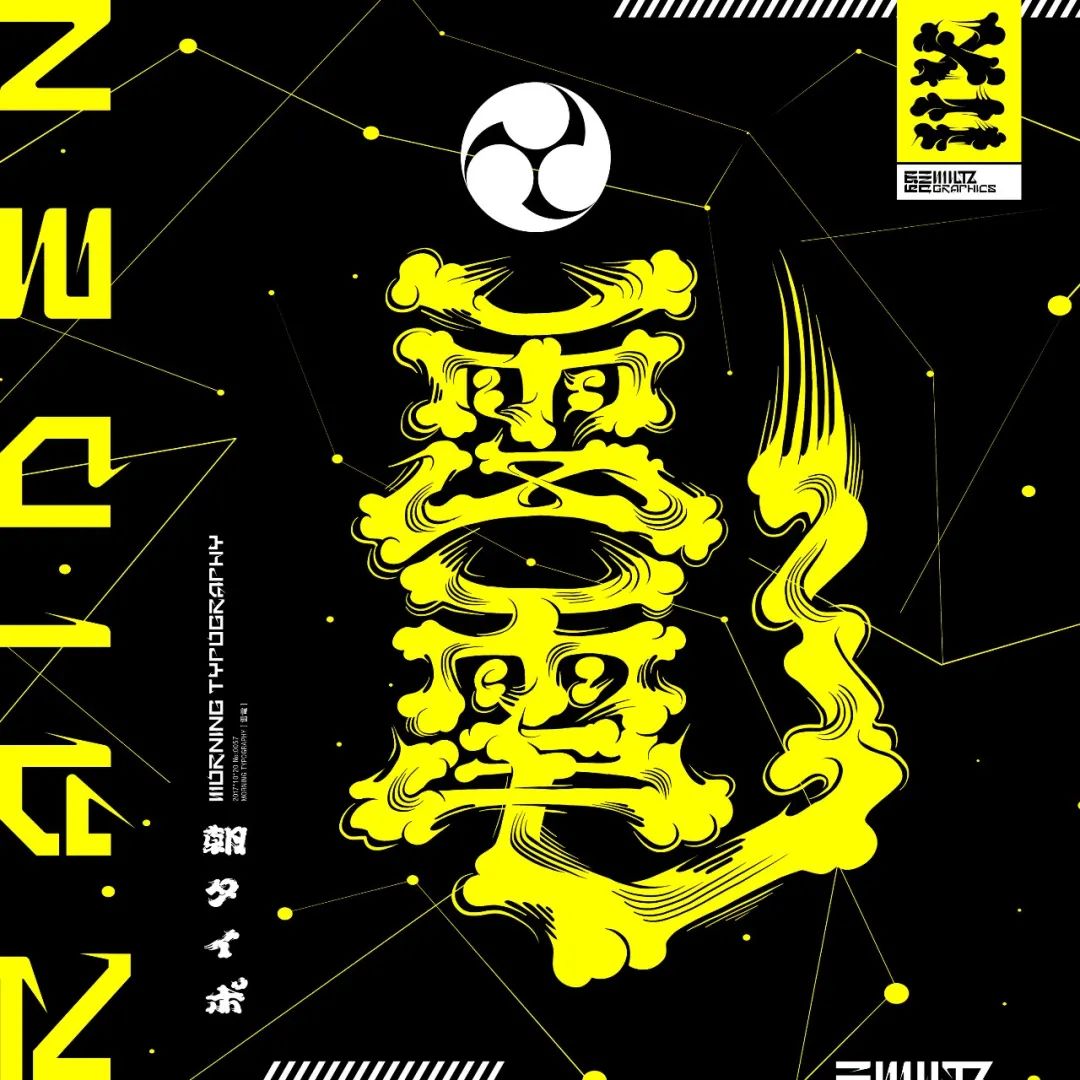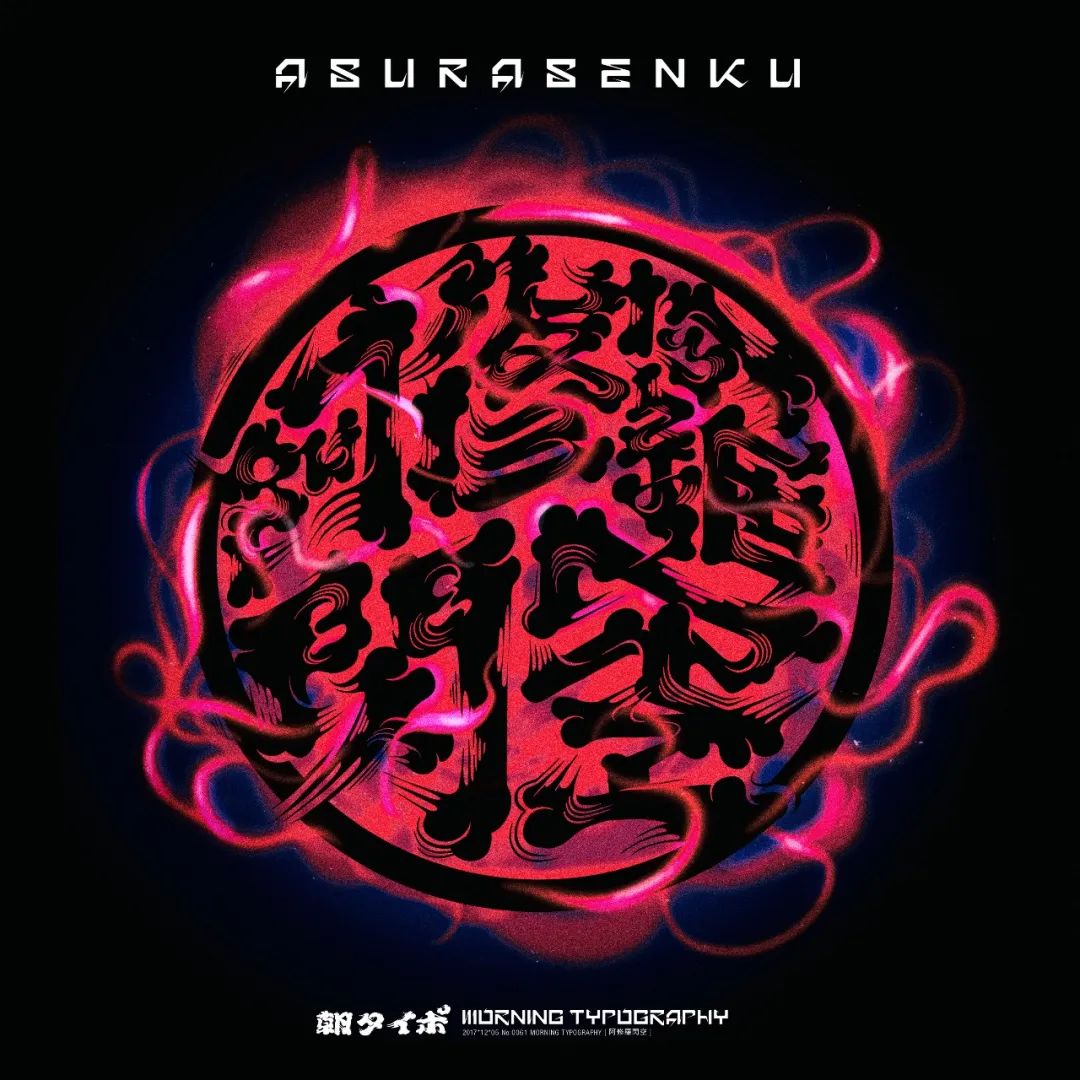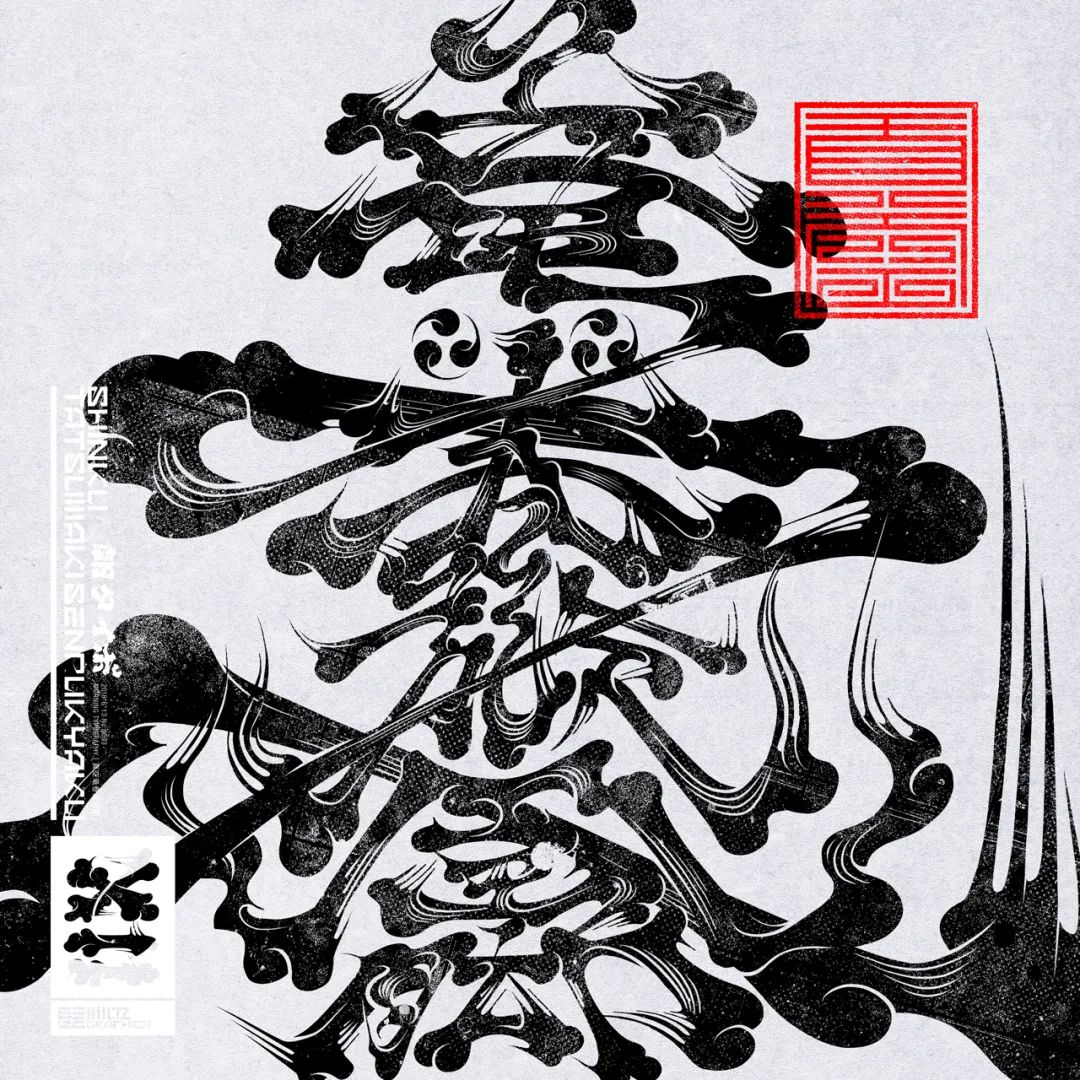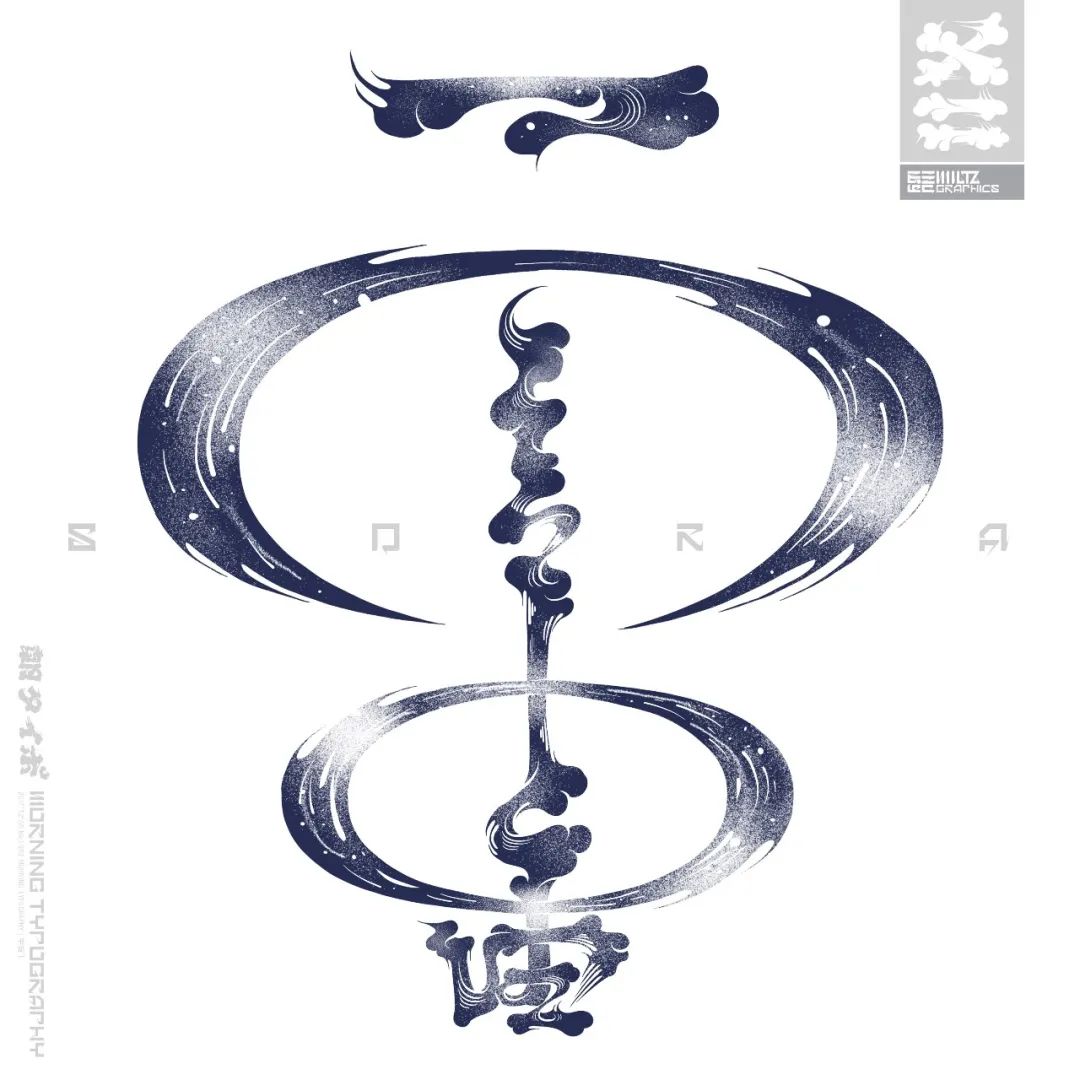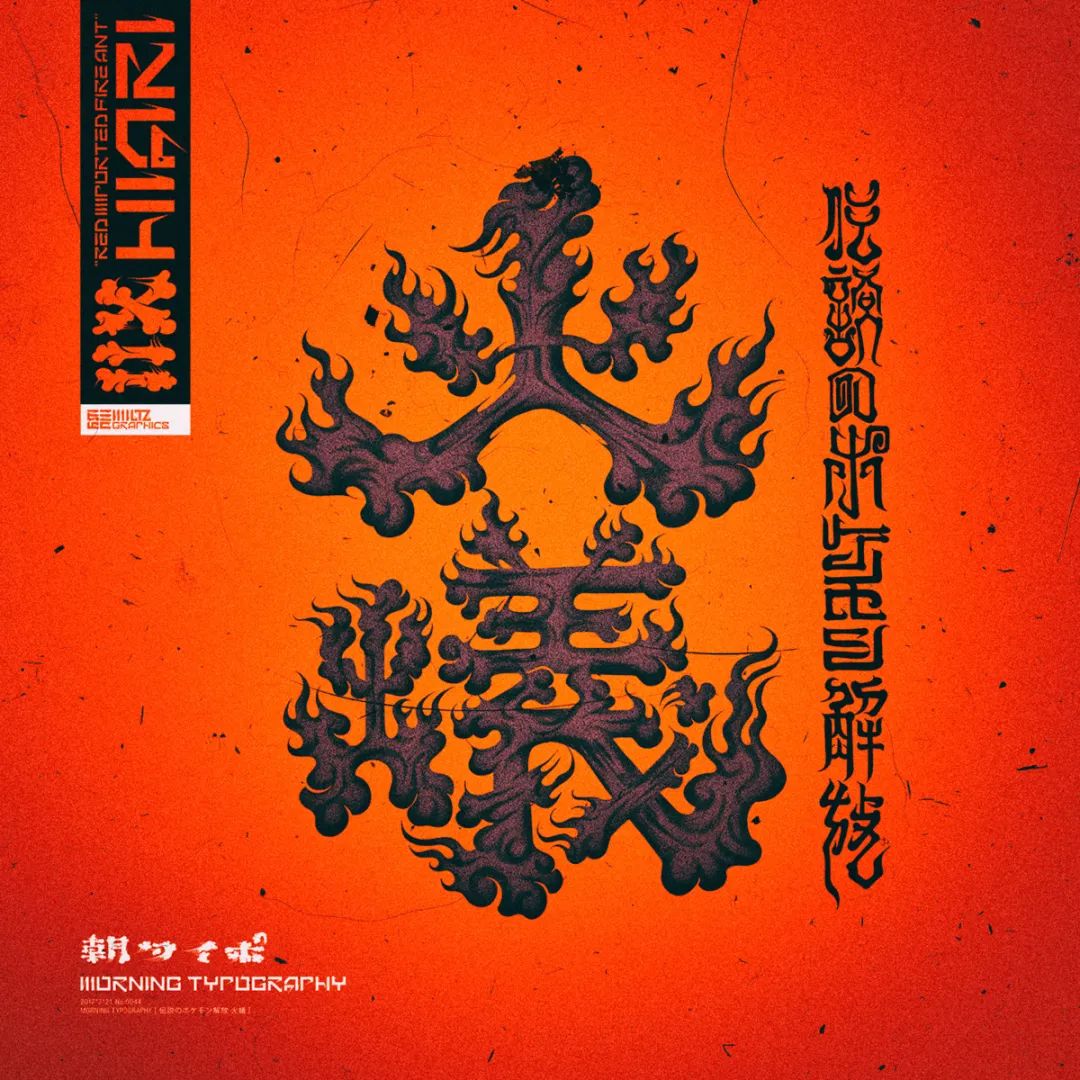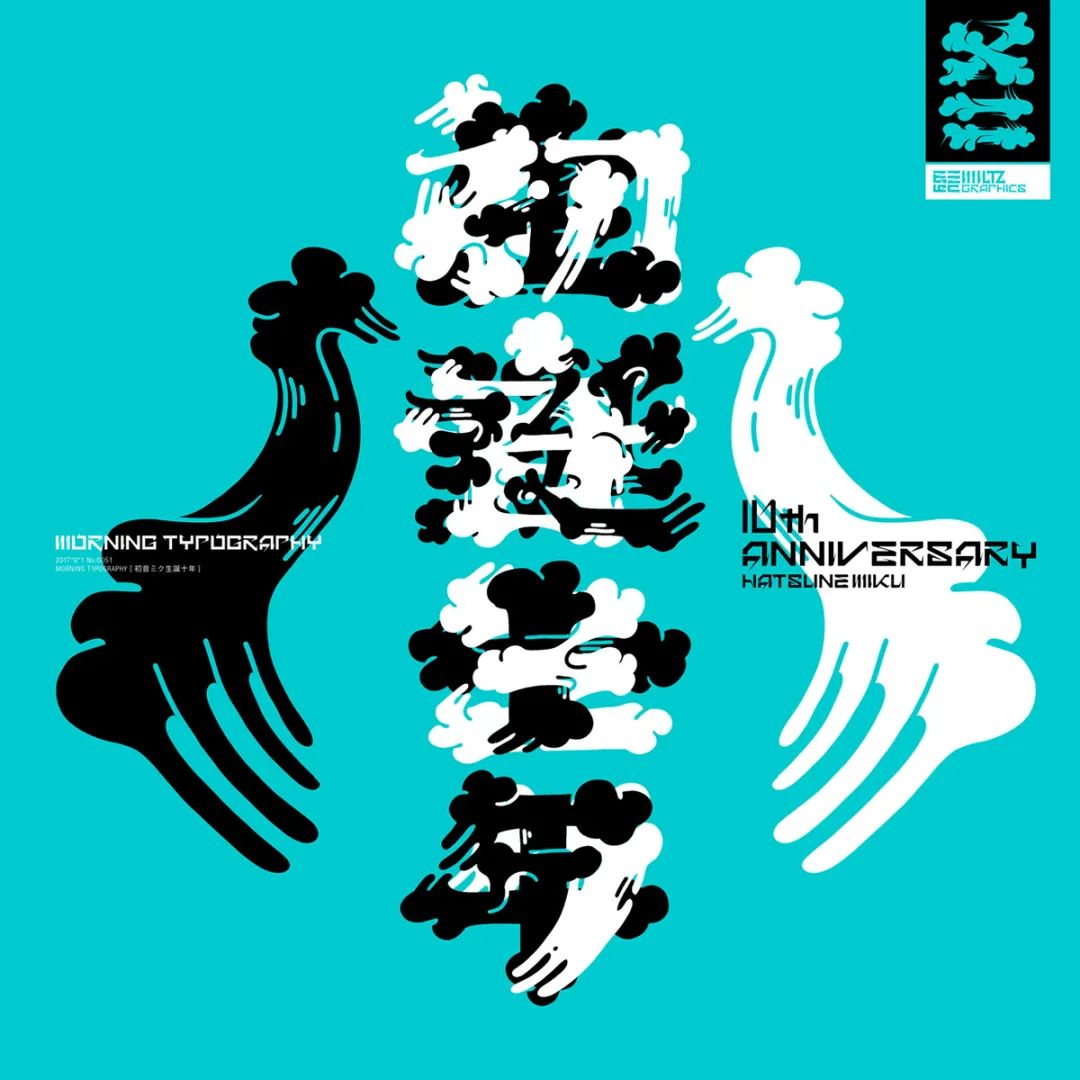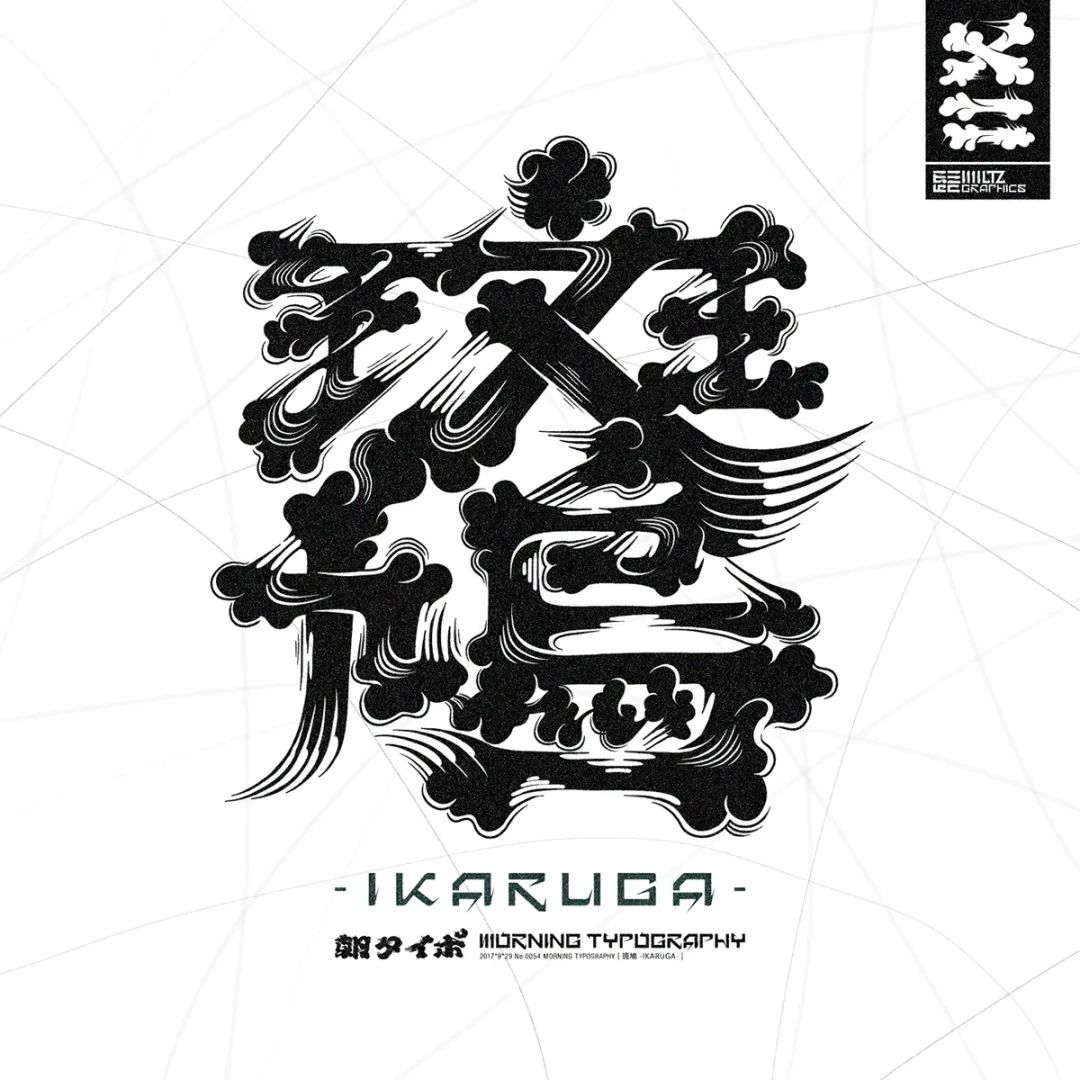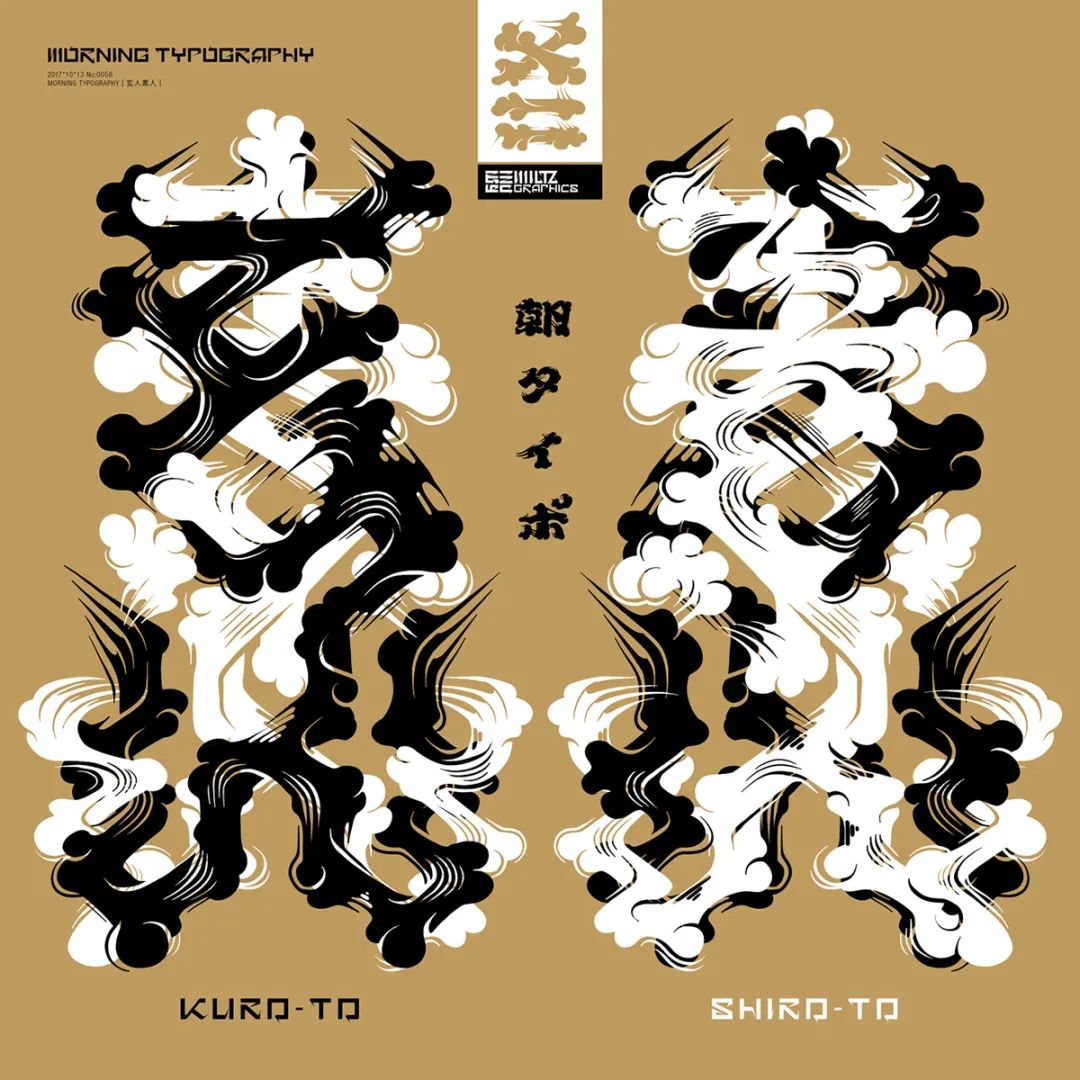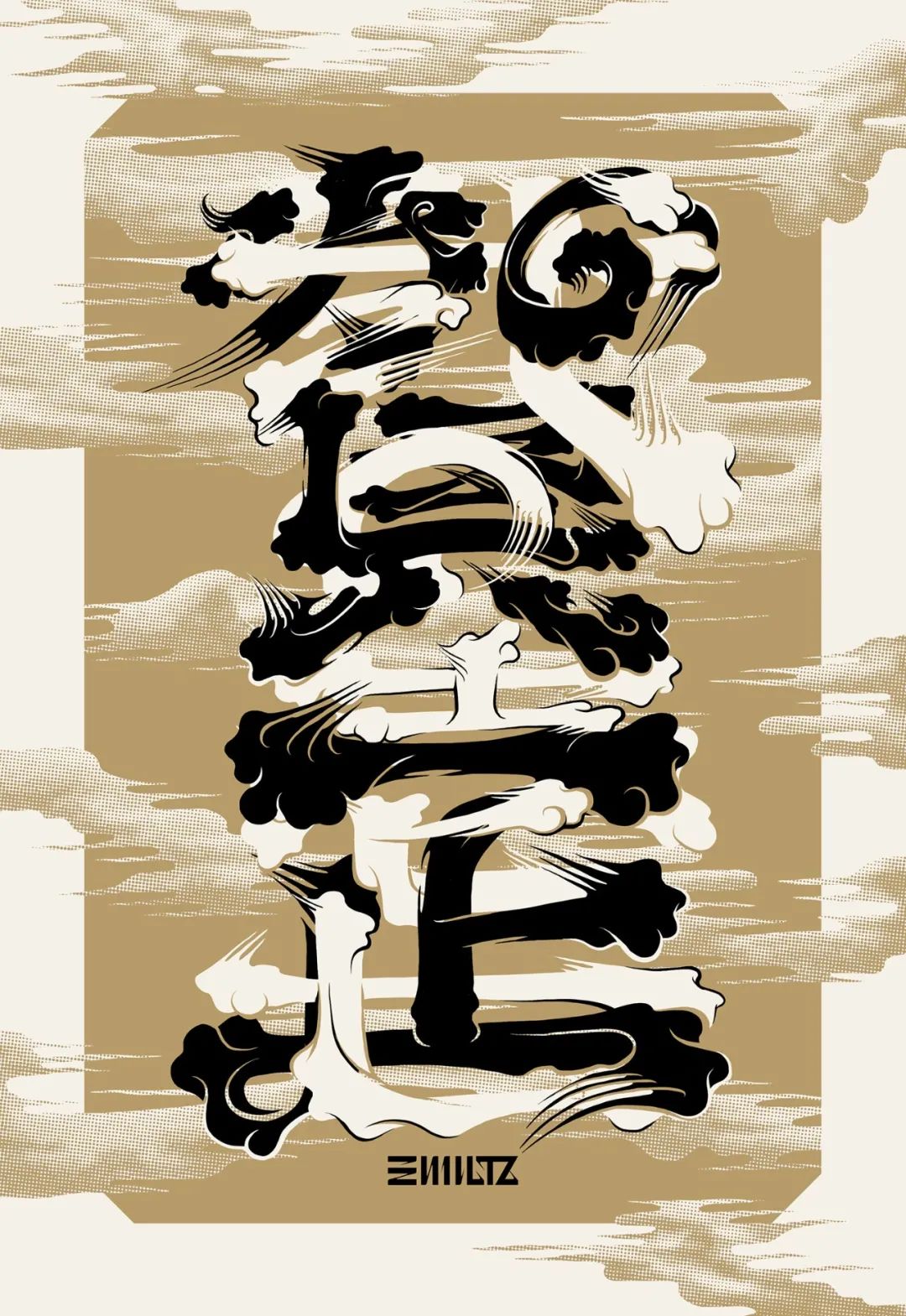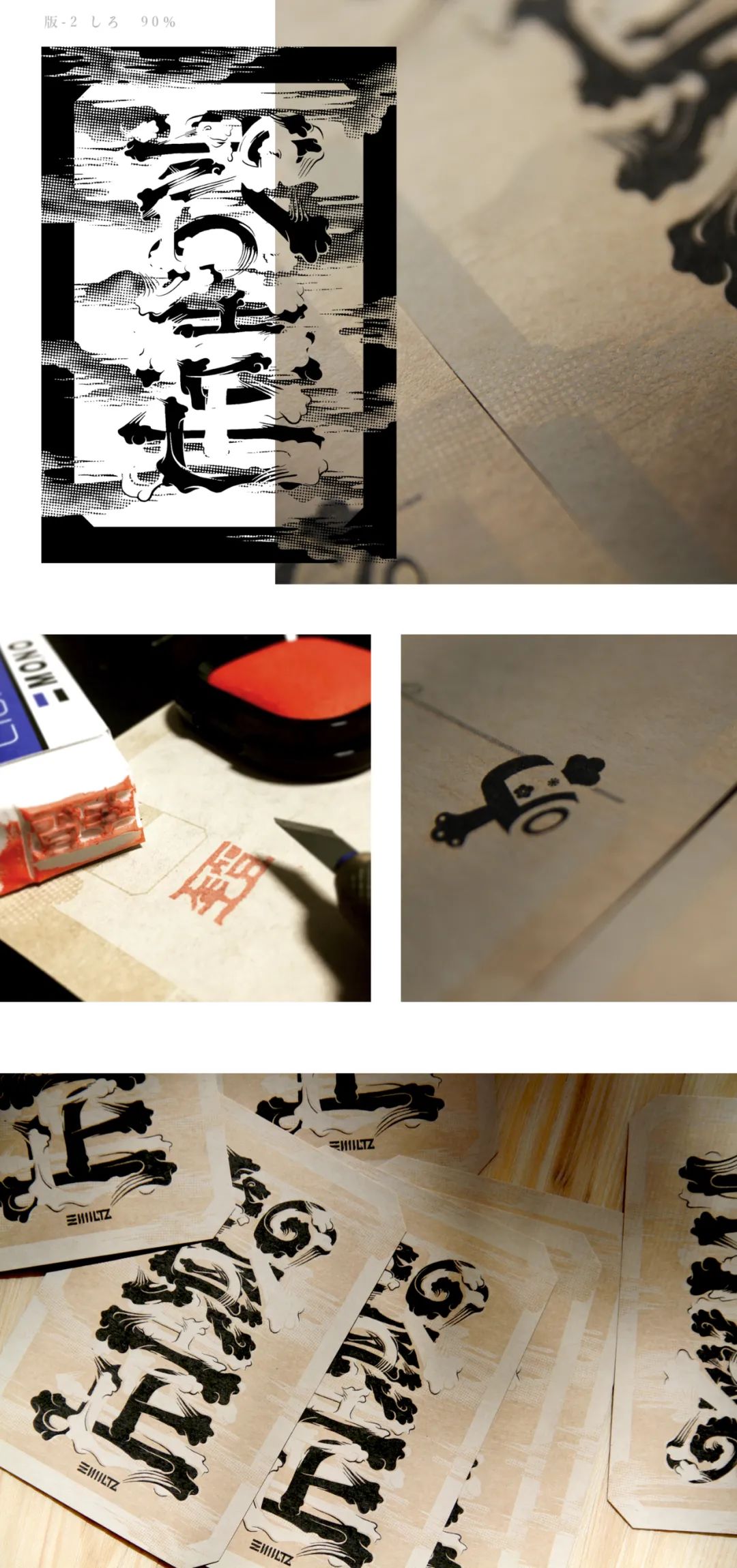
日本设计大神——MILTZ
他从书法和涂鸦艺术获取灵感
创造了名叫“KANJI-LINE”的
特殊图形字体风格
像骨头又像烟雾
雷 電
阿修羅閃空
邊
真空竜巻旋風脚
宇 宙
火 蟻
夜 空 交 差
熱 光 學 迷 彩
初音未来诞生十周年
斑 鳩
素 人 玄 人
贺 正
恶
疾 风 怒 涛
乱れ雪月花
千乃麻豆富
歪 み
GOKOU&SumiGOKOU